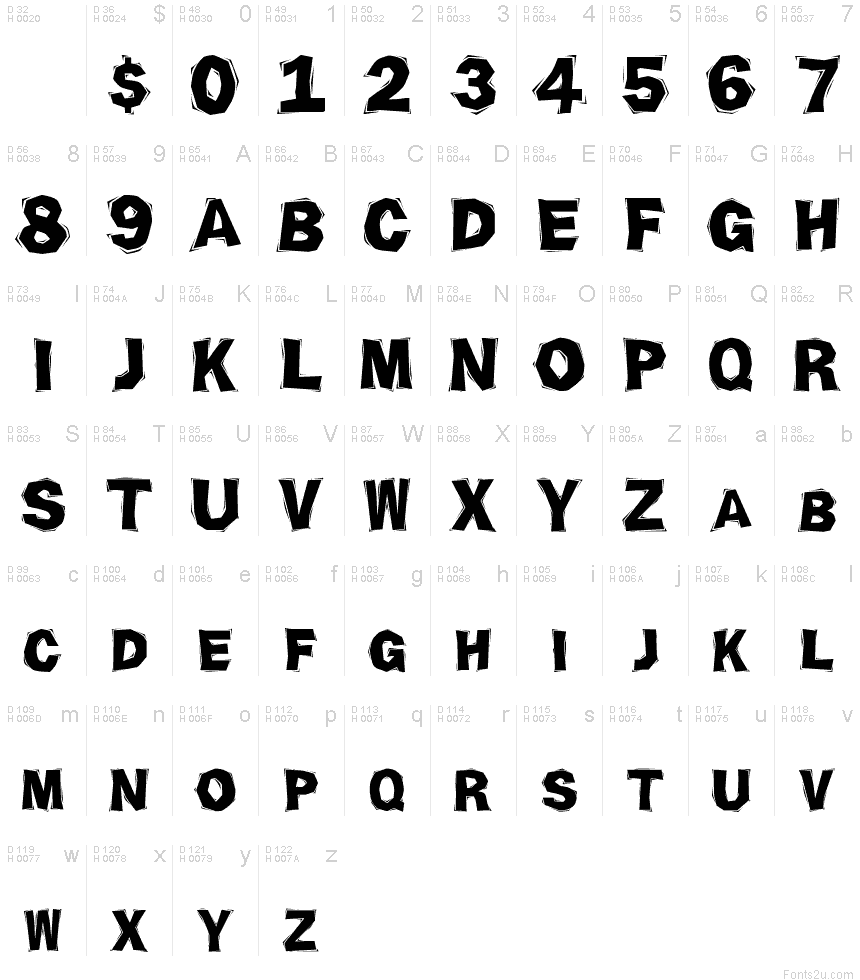
Crack Boum autorstwa Melle Derieppe Claude to darmowy komiksowy krój pisma typu display, zbudowany z masywnych, nierównych wersalików. Litery wyglądają jak wycięte z szorstkiego papieru – mają krzywe krawędzie, tępe narożniki i nieregularne grubości kresek, które nadają kształtom mnóstwo dynamiki. Nic nie jest tu mechanicznie uporządkowane.
Ten rękodzielniczy charakter świetnie odnajduje się zarówno w materiałach dla dzieci, jak i w oprawie graficznej projektów muzycznych, dzięki czemu sprawdzi się w tytułach gier, na okładkach albumów oraz na plakatach wydarzeń pełnych hałasu, żartów czy akcji. Krój pasuje również do opakowań przekąsek i zabawnych gadżetów, gdzie jego poszarpane sylwetki mogą nawiązywać do podartych etykiet, komiksowych efektów dźwiękowych, surowo zmontowanych ilustracji oraz ręcznie robionych maskotek.